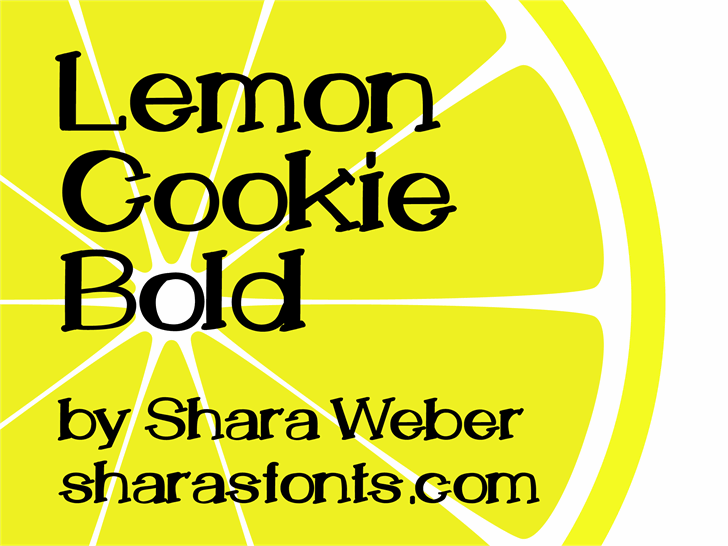
A fonte ‘LemonCookie Bold Font’ é uma criação cuidadosamente pensada para designers apaixonados por personalidade e elegância ao mesmo tempo. Com suas linhas suaves e levemente irregulares, ela retrata um estilo de escrita manuscrita que transmite confiança e alegria ao mesmo tempo. A Hamilton desenvolveu esta fonte específica para quem busca uma aparição única, onde a personalização e a simplicidade se unem em harmonia para criar um design único e envolvente. Com sua correta aplicação, ‘LemonCookie Bold Font’ não apenas tornará seus materiais de design mais profissionais, mas também os tornará únicos e divertidos ao mesmo tempo. É perfeito para nomes de marca, textos legíveis em produtos personalizados ou qualquer conteúdo onde deseja que a sua mensagem fale com você e seu público de maneira direta e encantadora.